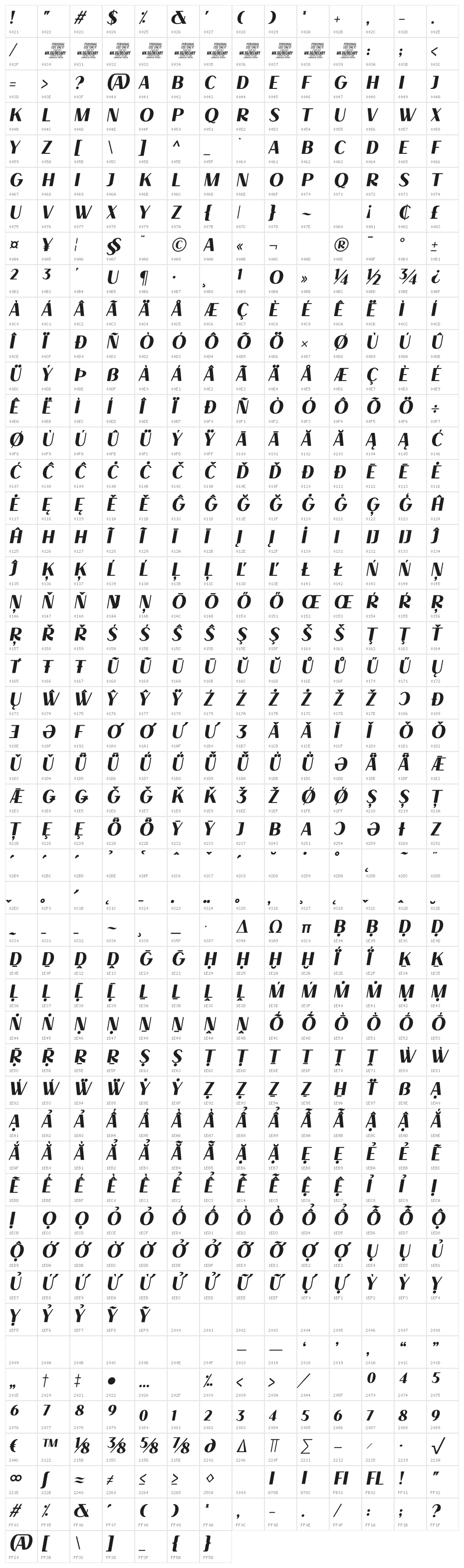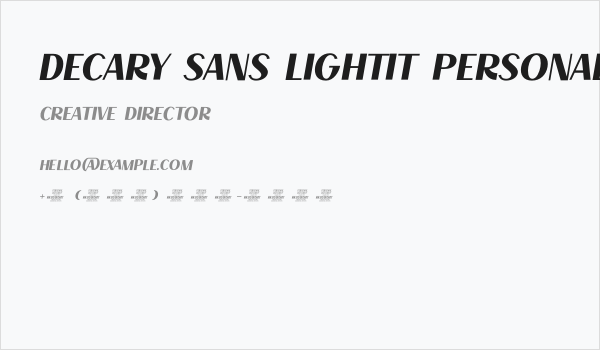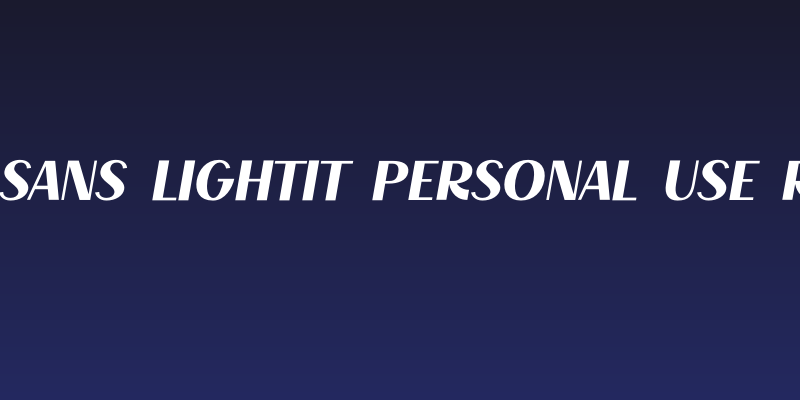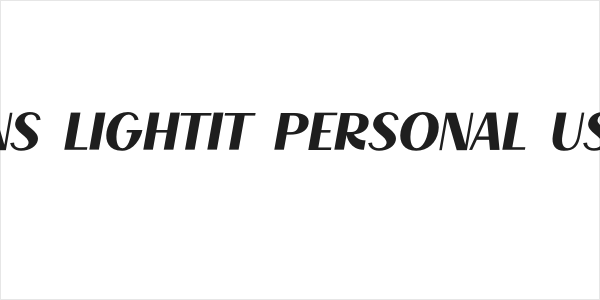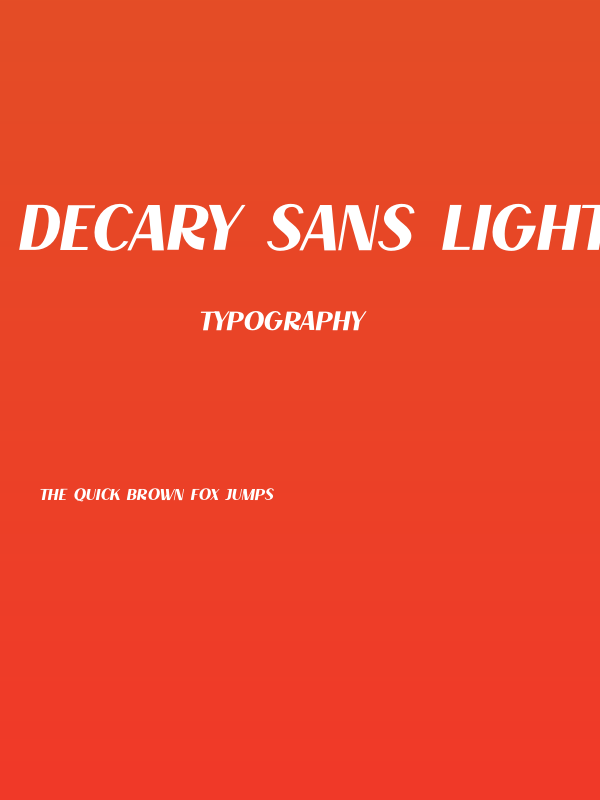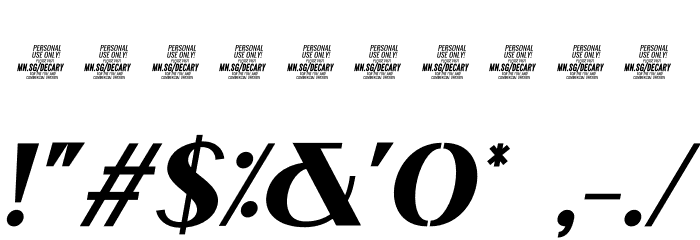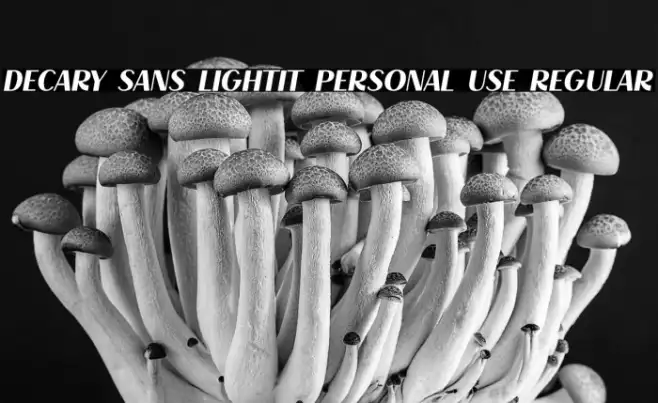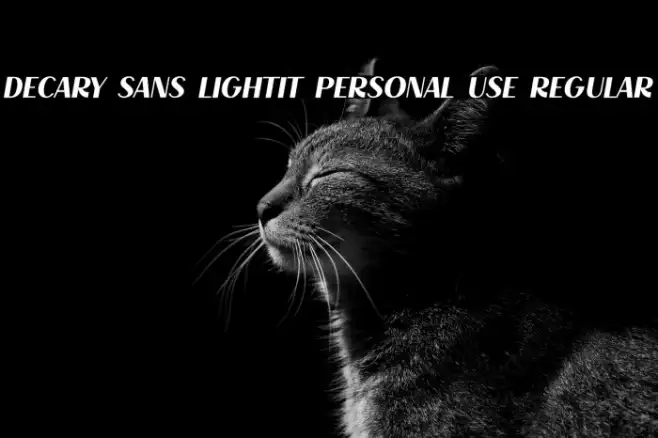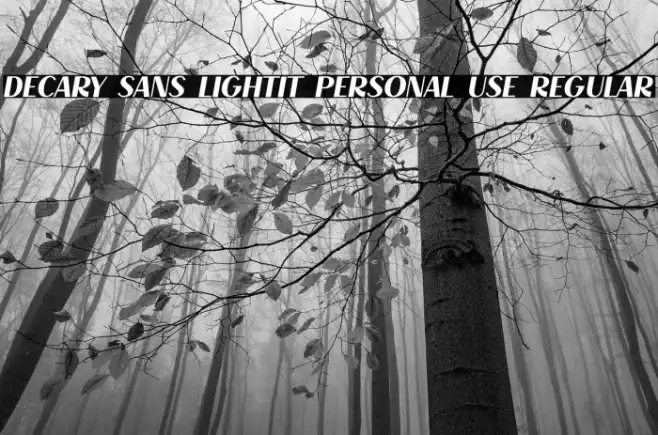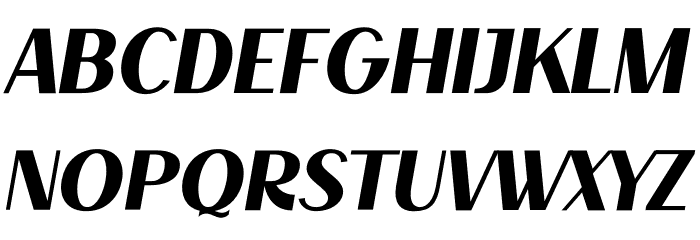
Decary Sans LightIt PERSONAL USE Regular Font
| Anwendungsfall | Headlines, Logos, Editorial design |
| Vorgeschlagene Projekte | Ideal for branding, advertising, and editorial design projects that require a modern and sophisticated touch. |